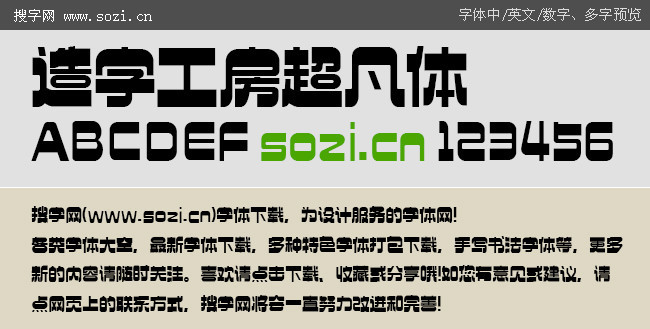
造字工房超凡體
搜字網(wǎng)給大家提供一款造字工房超凡體中文字體下載,造字工房超凡體筆畫粗細對比夸張、富于變化,拐角做圓弧處理,剛毅中又平添柔和,整體方正飽滿,視覺沖擊力強,力量感突出,節(jié)奏分明,充滿藝術(shù)張力。適用于大標題、包裝設(shè)計、海報設(shè)計等應(yīng)用。(本字體為個人非商用版,如需要商用請聯(lián)系官方購買版權(quán))